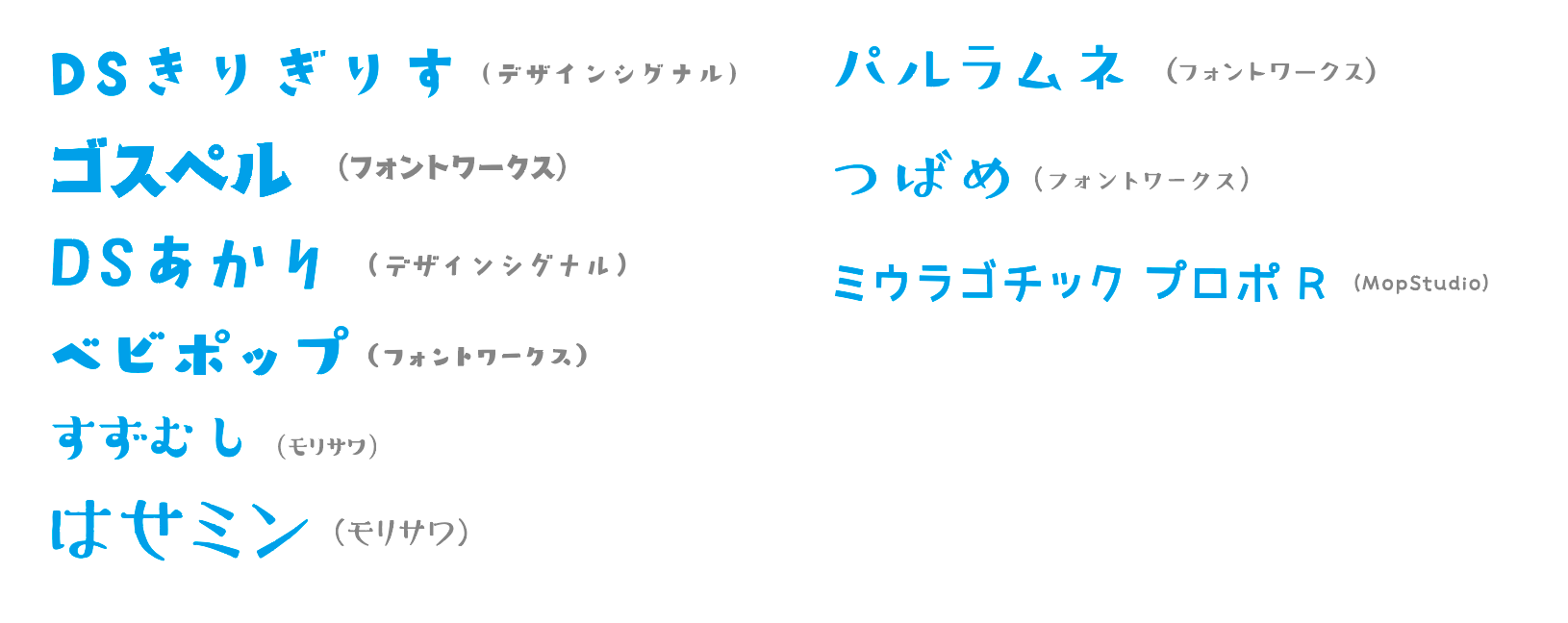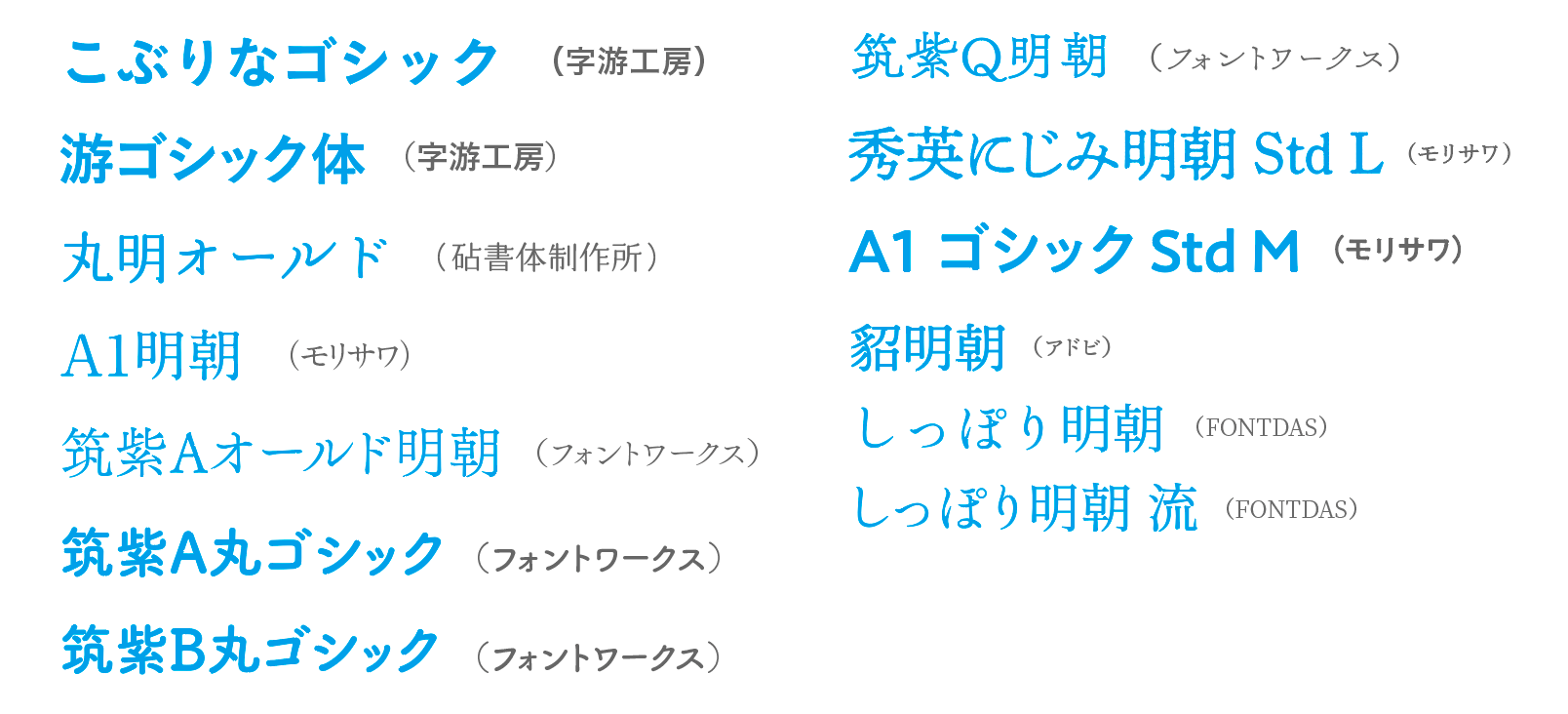
フォント関連 2017年のまとめ
2017年のフォントやテキストまわりについてまとめてみました。
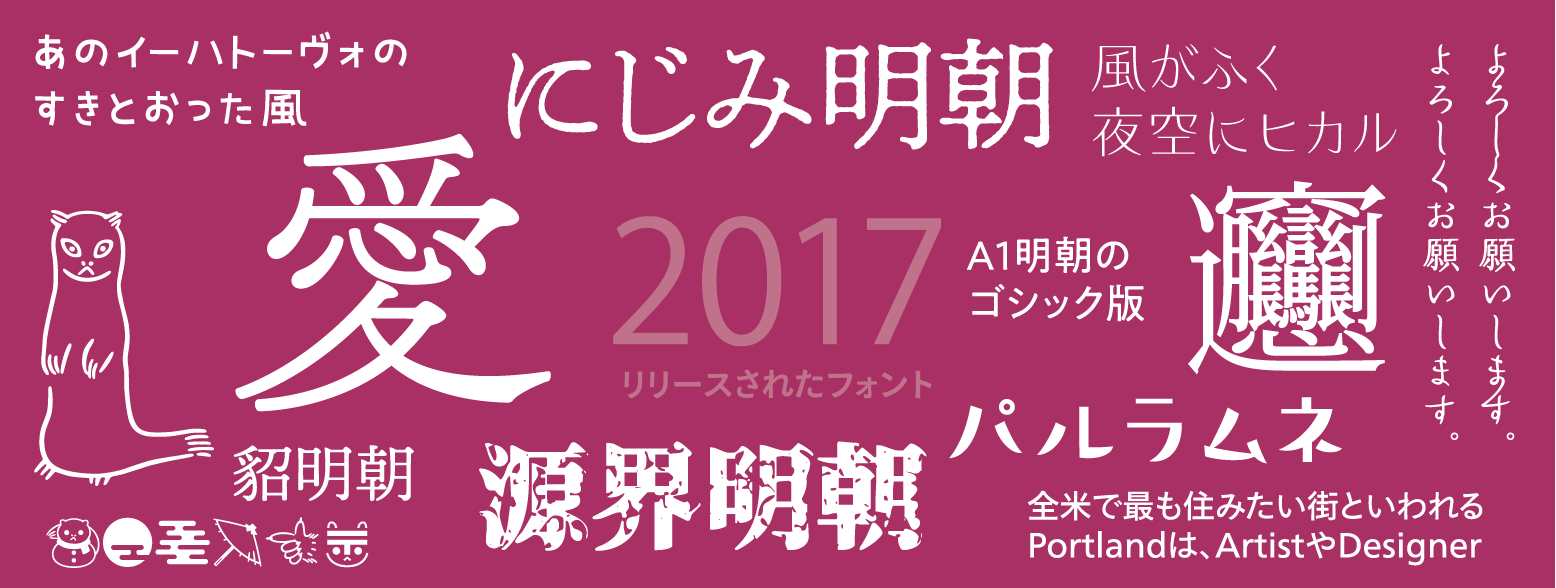
TV番組「マツコの知らない世界」にフォント特集が組まれたり、「フォントかるた」がヒットし、一般紙でも取り上げられるなど、フォントに対する注目度が高まった1年でした。
また、源ノ明朝のリリースに合わせて、4月10日が「フォントの日」(ダジャレ的な語呂合わせ)に登録されました。
新書体
定番のLETS、MORISAWA PASSPORTの新書体の加え、多くのフォントがリリースされました。
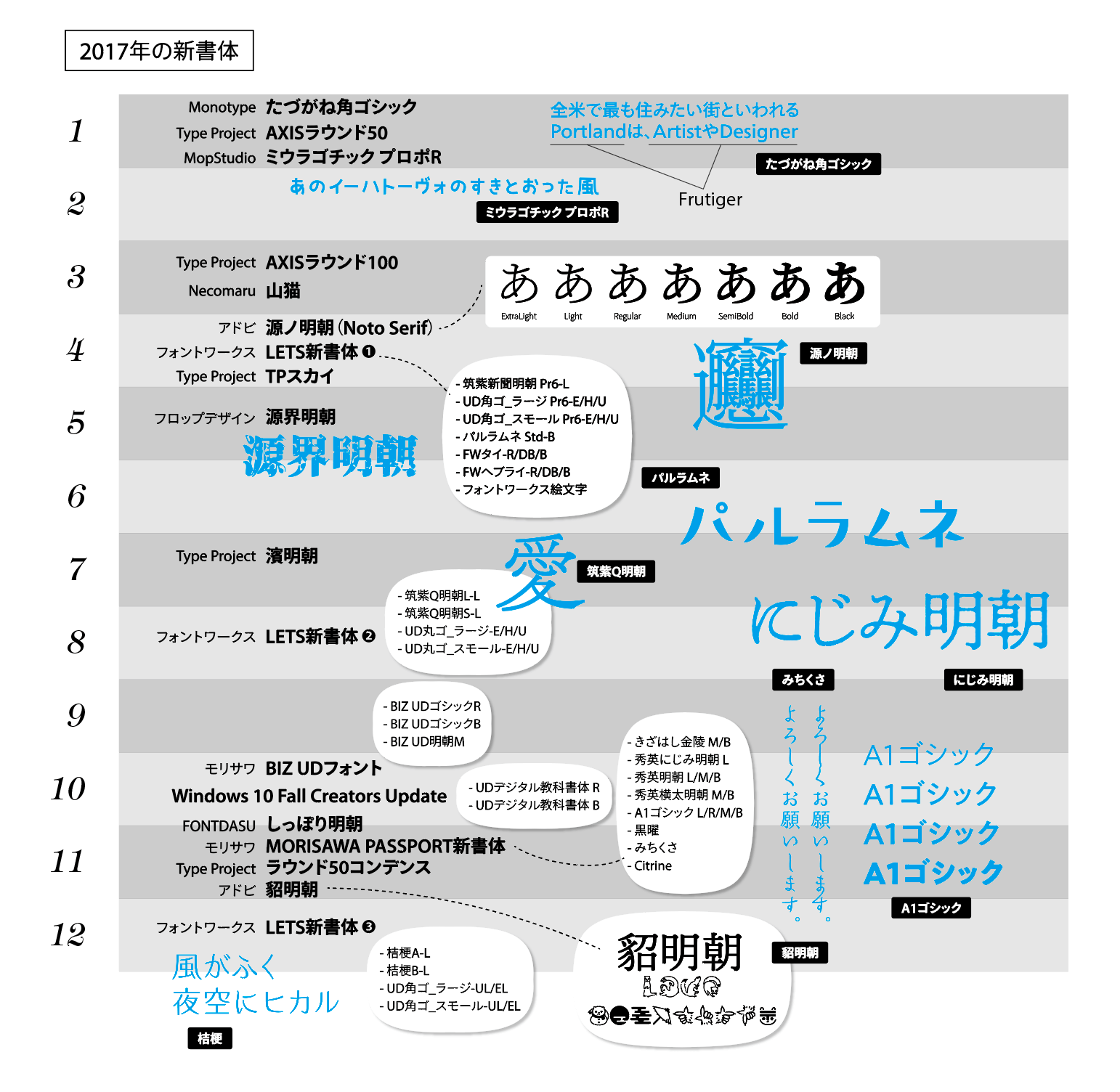
- LETS新書体は、4月、8月、12月の3回リリース。7月には秀英体17書体も加わりました。
- 4月
- 筑紫新聞明朝 Pr6-L
- UD角ゴ_ラージ Pr6-E/H/U
- UD角ゴ_スモール Pr6-E/H/U
- パルラムネ Std-B
- FWタイ-R/DB/B
- FWヘブライ-R/DB/B
- フォントワークス絵文字
- 7月(秀英体17書体)
- 秀英明朝L(細)
- 秀英明朝M(中太)
- 秀英明朝B(太)
- 秀英初号明朝
- 秀英横太明朝M(中太)
- 秀英横太明朝B(太)
- 秀英アンチック
- 秀英四号かな
- 秀英四号太かな
- 秀英角ゴシック金L(細)
- 秀英角ゴシック金M(中太)
- 秀英角ゴシック金B(太)
- 秀英角ゴシック銀L(細)
- 秀英角ゴシック銀M(中太)
- 秀英角ゴシック銀B(太)
- 秀英丸ゴシックL(細)
- 秀英丸ゴシックB(太)
- 8月
- 筑紫Q明朝L-L
- 筑紫Q明朝S-L
- UD丸ゴ_ラージ-E/H/U
- UD丸ゴ_スモール-E/H/U
- FWアラビア-R/DB/B
- FWヒンディ-R/DB/B
- 12月
- 桔梗A-L
- 桔梗B-L
- UD角ゴ_ラージ-UL/EL
- UD角ゴ_スモール-UL/EL
- 4月
- MORISAWA PASSPORT新書体は11月にリリース
- きざはし金陵 M/B
- 秀英にじみ明朝 L
- 秀英明朝 L/M/B
- 秀英横太明朝 M/B
- A1ゴシック L/R/M/B
- 黒曜
- みちくさ
- Citrine L/R/M/B (98言語をサポートする独自規格、A1ゴシックとの和欧併記を目的に作られ、墨だまりや角丸処理といった共通のエレメントを採用)
- ヒラギノ角ゴ W1/W2/W4/W5:文字セットをProN(Adobe-Japan1-5)に拡張
- ヒラギノ角ゴ 繁体中文 W3/W6
- アドビからは2書体
- 源ノ明朝(4月)
- 貂明朝(11月)
- Monotypeから「たづがね角ゴシック」がリリース(Frutigerに合う和文フォントとして話題に)
- モリサワからビジネスユース向けのUDフォント「BIZ UDフォント」がリリース。先行リリースの3フォントは無料(来年以降に拡大)
- BIZ UDゴシックR
- BIZ UDゴシックB
- BIZ UD明朝M
- Windows 10 Fall Creators Updateで「UDデジタル教科書体 R/B」(モリサワ)が搭載(10月)
その他の新書体
まとめ
新書体 来年はどんなフォントがリリースされるか楽しみですね。
筑紫Q明朝
リリース前から文字っ子界隈で話題になっていた筑紫Q明朝がリリースされました。
源ノ明朝
2015年にリリースされた「源ノ角ゴシック」の明朝版、「源ノ明朝」が4月10日、「フォントの日」にリリース。「源ノ角ゴシック」同様、7ウエイトで展開される無料フォント。
オープンソースのため、源ノ角ゴシック同様、これを改変したフォントがどんどんリリースされています。Google版の名称は「Noto Serif」です。
| ゴシック | 明朝 | |
|---|---|---|
| アドビ | 源ノ角ゴシック | 源ノ明朝 |
| Source Han Sans | Source Han Serif | |
| Noto Sans CJK | Noto Serif CJK | |
| リリース | 2015年7月 | 2017年4月 |
ビャンビャン麺の「ビャン」
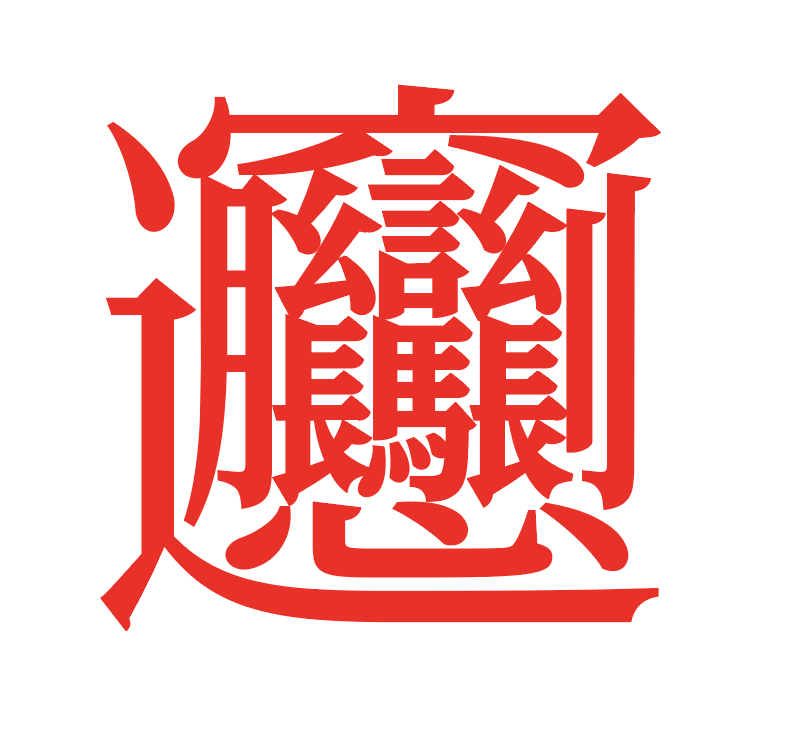
源ノ明朝は、漢字の中でも一番画数が多いビャンビャン麺の「ビャン」をサポートしていることも注目を集めました。
「⿺辶⿳穴⿰月⿰⿲⿱幺長⿱言馬⿱幺長刂心」を入力して、フォントを「源ノ明朝」または「Noto Serif」に設定すると「ビャン」(ビアン)の漢字になります。
貂明朝
Adobe MAX Japan 2017に併せて、アドビから「貂明朝(てんみんちょう)」がリリースされました。オールドっぽいテイストのあるかわいらしいフォントです。なお、来年のアップデートでカラーフォントとして利用できるようになるようです。
絵文字、アイコンフォント
ハンバーガーの絵文字
Androidに搭載されている絵文字の「ハンバーガーのチーズの位置が違うのでは?」「ビールのジョッキが満杯でないのに、泡があるのはおかしい」というツッコミが入り、およそ1ヶ月でアップデートされました。
Font Awesome 5
Font Awesome 5の正式版がリリースされました。LINEのアイコンが増えるほか、Proバージョンもリリースされています。
アドビ(Illustrator、Photoshop、InDesign)
Typekit
9月に74の和文フォントが追加。これで和文フォントは、88ファミリーになりました。こうなると、「同期でるのは100書体まで」という制限が厳しい。
サイト利用者、日々の運用、制作会社、表現に関して、次のようなメリットがあります。
- スケーラブル(デバイスを問わず、シャープに表示できる)
- 色変更に対応できる(反転するなど)
- テキストを選択、コピーできる
- 多言語展開しやすい(ユーザーがブラウザー上で翻訳することも可能)
- メンテナンス性が高い(テキスト変更やパーツの追加)
- 検索対象になる(SEO効果)
- 文字詰め可能
- プリントメディアとの整合性をとりやすい
ウェブフォントの悪い点
表示速度、費用、組版(美意識と可読性)などの点で懸念すべき点があります。
- 費用がかかる
- 本文なのに、句読点を詰めてしまうと読みにくい
- 書体が主張しがち(ないように)
- Windows環境でのレンダリングがキレイでない
- 速いといっても、環境によっては読み込みに時間がかかる
FONTPLUS、TypeSquareは、コントロールパネルで文字詰めをオンにすることができます。句読点も詰まってしまうので、本文には不向きです。
また、フォント指定に不慣れが方が使いはじめると、多様なフォントを使い過ぎてしまうことがあります。